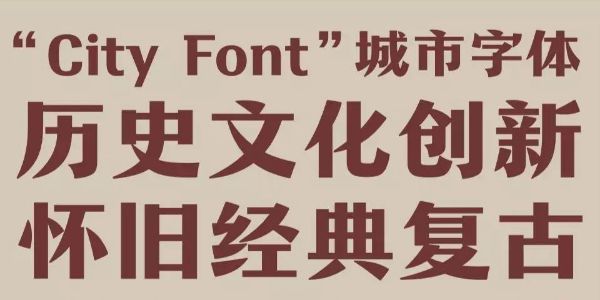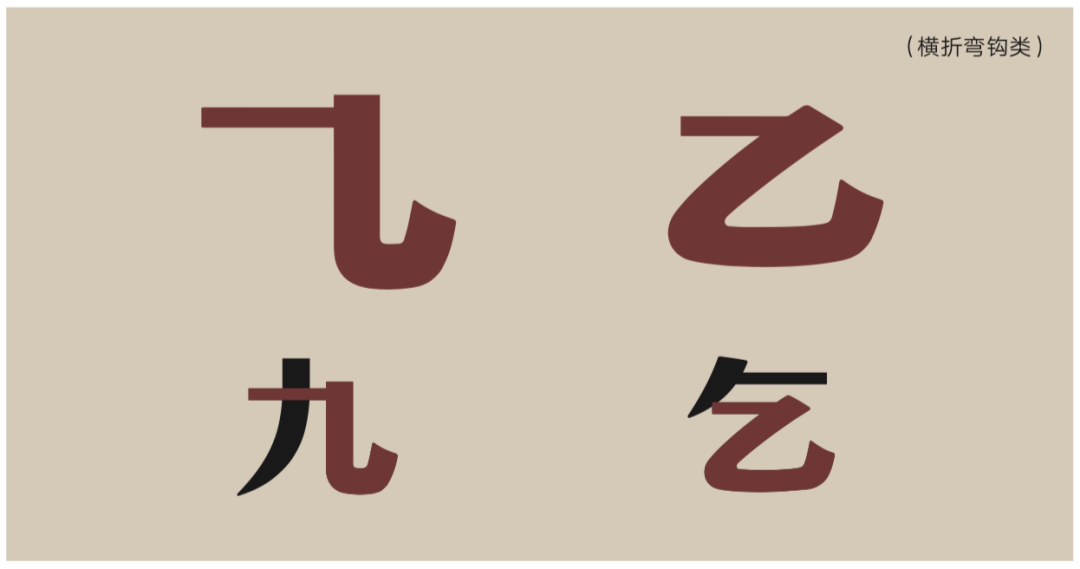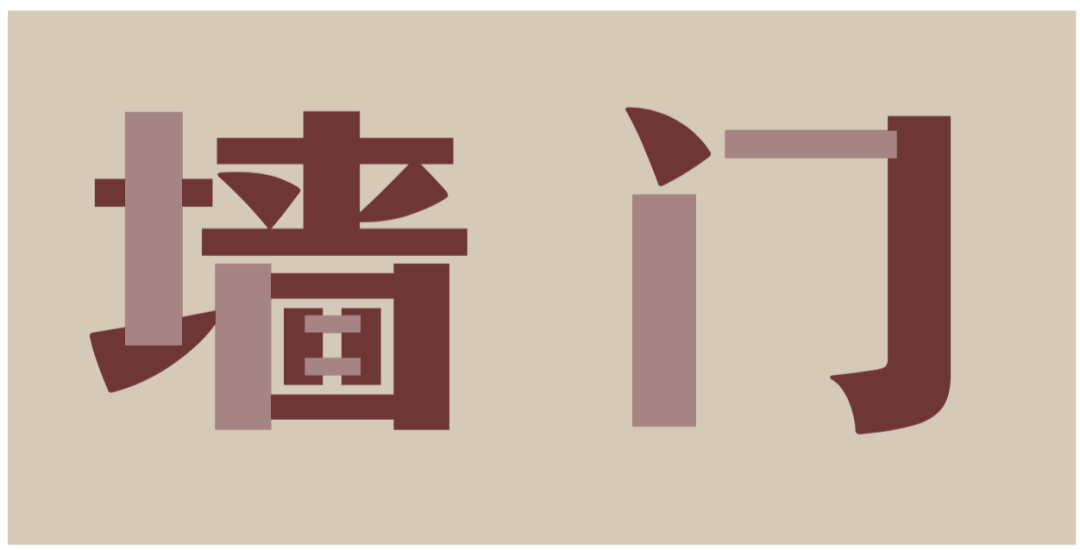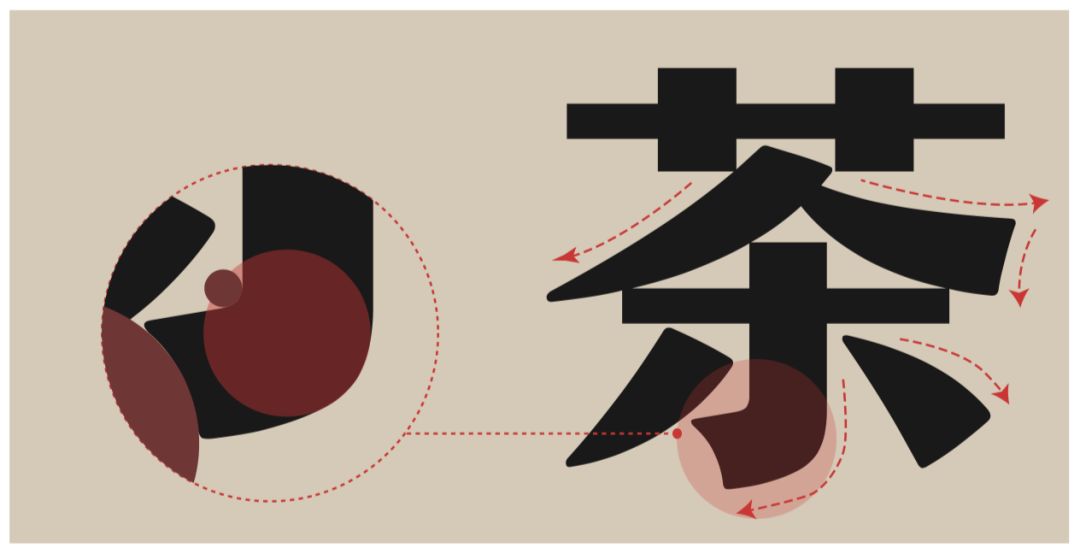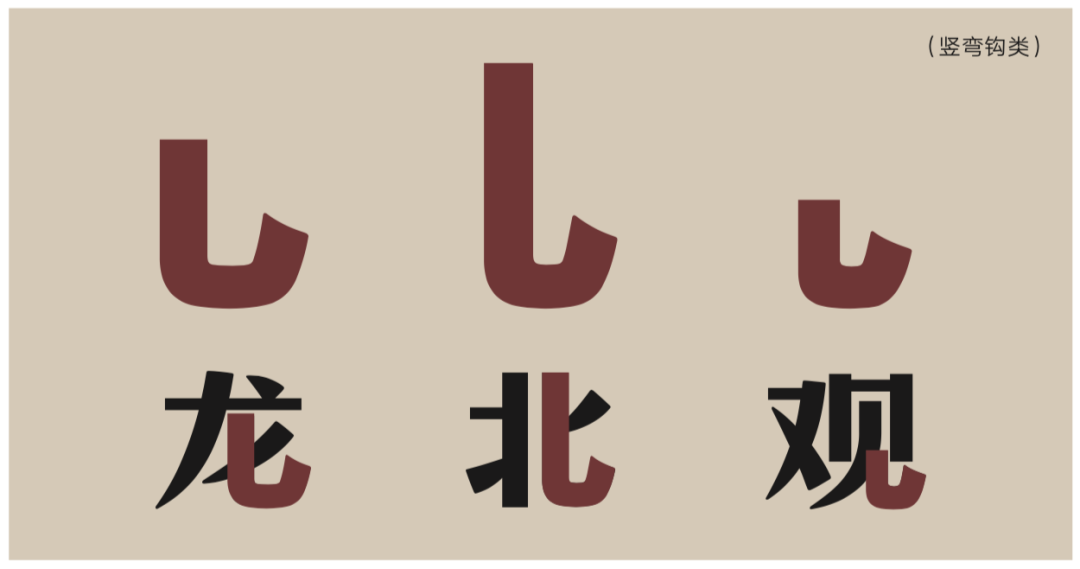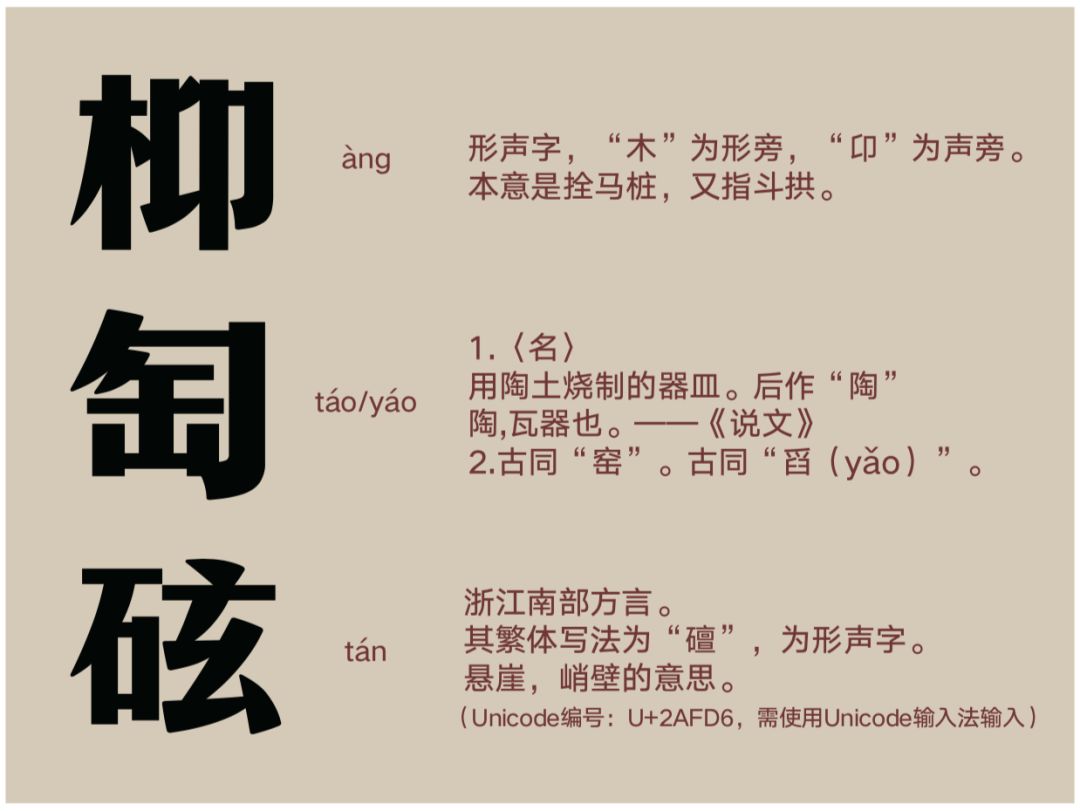
透过一款字体,书写一座城市
今天,字由上线了一款特殊的字体,它就是中国首款城市字体——汉仪松阳体。
它是由著名设计师吴勇&汉仪字库高级字体设计师刘宇共同设计,经汉仪字库艺术顾问、著名字体设计师朱志伟指导,在松阳县政府的支持下完成的。
曾经,几乎中国的每一个城市都有其门牌字体。从老上海、北京、南京、广州到各个市县行政区,各自制作,因此百花齐放,各有特色。
如今,千篇一律的街牌布满了全国,上面的字体是毫无温度的通俗字体。我们越发怀念这些老旧的字样,它们源于 " 秀才 " 们一笔一画端端正正的书写,蕴含了每条街道、每户人家内心最朴实美好的心愿。它们那么美,如今在时代的洪流中却似是不曾来过。
“汉仪松阳体”的字体基因就来源于松阳的老门牌,字体主创设计师吴勇老师行走在这座始建于明朝的老城中寻找设计灵感时,偶然发现这里的老门牌保留的异常完好,在千篇一律的现代黑体门牌中,显得格外的亲切,让人惊喜。
老门牌上的字体约造于上世纪六七十年代,书写大气厚重且笔画设计游刃有余,虽不足百年历程,但它的形成与历史积淀却象征着松阳文脉链中的精神所在,凝聚成这座小城独特的“文化气质”,成为了市井文化中最鲜活的“化石”。
我们将对松阳的感受与老门牌字体风格相结合,打造出一款属于松阳的城市字体——汉仪松阳体,希望它的诞生,能够让这座城市的文化更加鲜活。
这款字体在结构上提炼了门牌字的特点,整体风格怀旧淳朴,有着老城区的质感。
9169中文简繁+当地常用字+拉丁字符,汉仪松阳体字形偏扁,稳重有力,大气敦厚但不笨拙,中宫微收,字面饱满,宽博挺拔,有一种直爽硬朗的宋黑体味道。
笔画设计保留了松阳街道小巷里门牌字样的字体感觉,与印刷字体平板僵直的感受不同,有着原始手工质感和时间的烙印感。尤其是在撇、捺、钩、提的处理上,很有弹性、有精神。
运用不同弧度的曲线,使笔画圆润但有力。
钩的形态也丰富多样,在表现笔画厚实、有弹性的基础上,根据空间大小,有不同的诠释。
汉仪松阳体的西文字体与中文字体风格统一,有着相同的装饰衬线,字母粗细对比明显。
汉仪松阳体除了常规字符集JFW外,还额外多出了三个生僻字,这是它的不同之处。
这三个生僻字来源于松阳县老街门牌和当地名人的姓名,是独属于那个时代的视觉记忆与文化表征。其中的“石玄”字,现时的字典和输入法中均未收录。如今我们将这些字收录在“汉仪松阳体”中,使它们能够继续在“松阳文化”中流传下去。
排版效果
原本作为门牌字的字体结构就非常清晰,易于识别,通过设计师的再次设计改进后,字体的笔画粗细对比更加鲜明,空间结构布局更合理,再加上它笔画无饰角,字形严谨不失松快,具有良好的标牌易读性。
“汉仪松阳体”也将被运用到古村落群的导视系统中。质朴的人文气息与村落交相辉映,似乎平淡的生活中又充满了趣味,隐隐的散发着让人向往的魅力。
字体和建筑,在对历史的尊重和对文化的创新双重精神照耀下,相得益彰,熠熠生辉。
城市字体“汉仪松阳体”诞生后,既能够存在于有形的导视系统,带你游览这座城的景色,又能够无声地为你讲述这座城的故事,它独有的气质就像当地的方言,让你透过文字认识这座城,爱上这座城。